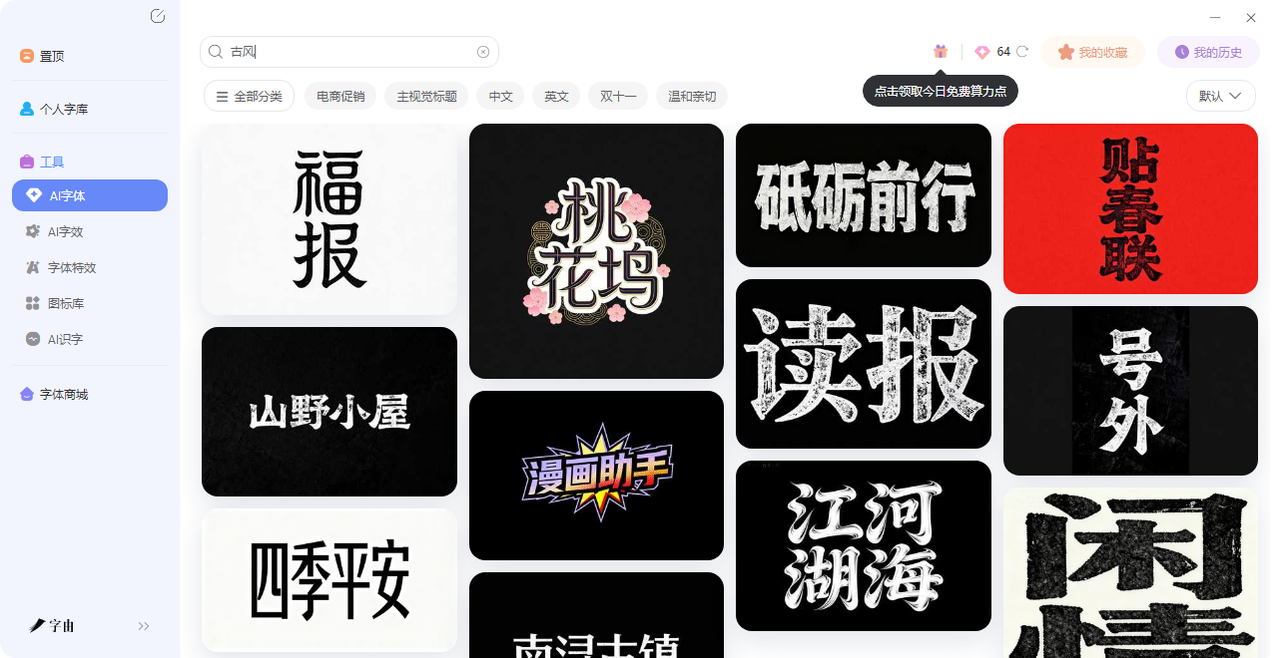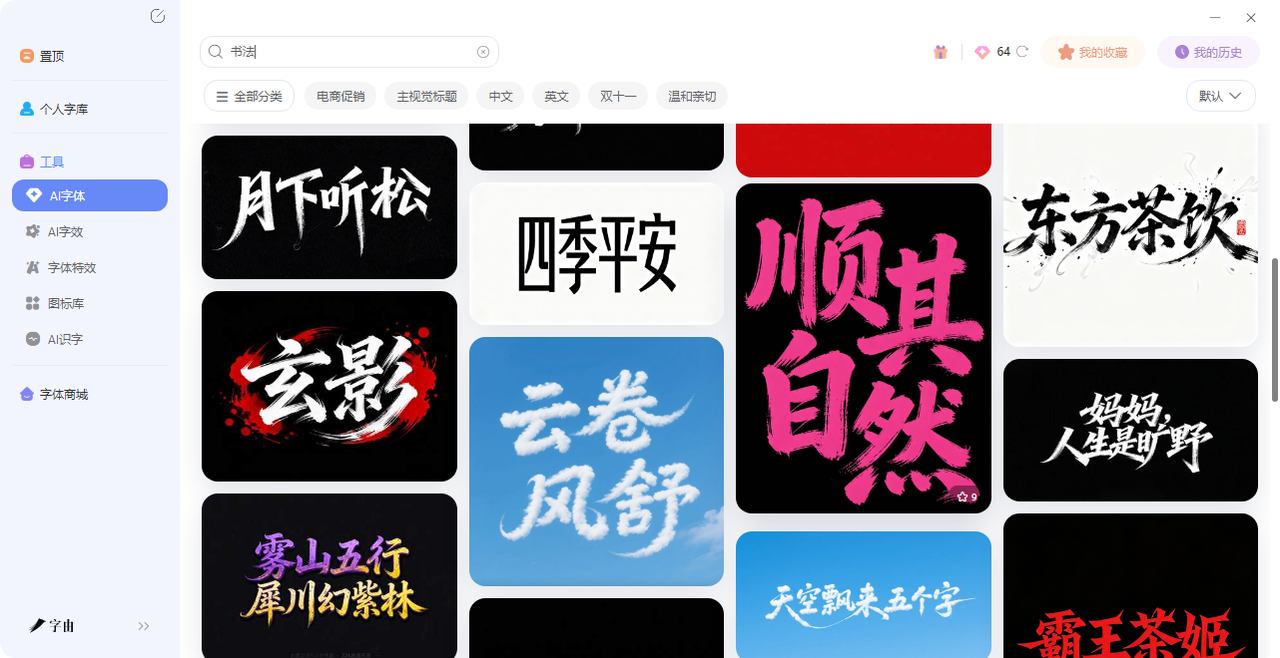
国潮艺术字、中式包装字体、古风Logo…一个网站全搞定
当你的甲方和你说想要国潮字体的时候,脑子里浮现出那种墨韵十足的书法标题,翻遍字体网站,要么是电脑味太重的“书法体”,要么是授权不明的免费字。想做一张国潮海报,标题想要那种笔锋凌厉、墨迹飞白的效果,自己不会写毛笔字,请人写又来不及。想做古风Logo,试了几十款字体,总觉得少了点味道,其实,古风书法字AI生成这件事没那么难,今天我就给大家推荐一款能够一站式解决国风字体需求的网站——字由。它的AI字体功能里藏着大量古风书法模板,输入文字,选个模板,几十秒就能拿到一张自带墨香的艺术字。做国潮设计、中式包装、古风Logo,一个网站全搞定。
字由的“AI字体”功能,不是让你自己去调参数、做设计,而是把成千上万种艺术字效果做成了模板。你只需要输入文字,选一个顺眼的模板,点一下生成,就能拿到一张高清艺术字图片。尤其值得一提的是,它的古风书法类模板,数量多、风格全,几乎覆盖了你做国潮设计可能需要的所有方向。接下来我会把AI字体里面出现的一些我觉得比较好用的古风书法模板分类整理一下,方便你以后快速找到。
节气、季节类模板:
- “万物生长”:这个模板墨色有浓淡变化,适合做春季主题的海报、农产品包装、自然品牌Logo。
- “冬去春来”:字体偏行草,连笔流畅,适合做跨年、春节、四季主题的设计。
- “东极岛”:带着一点岛屿的辽阔感,笔画粗犷但不失韵味,适合做旅行目的地、民宿、海产品的包装或宣传物料。
- “芳华国色”:这四个字偏女性化,笔画柔美,墨迹细腻,适合做化妆品、汉服、国风礼盒的包装标题。
- “糖瓜粘”:这个名字很有意思,字体圆润可爱,带着童趣,适合做年货、糖果、传统小吃的包装。
励志、祝福类模板:
- “暴富”:粗笔大字,墨色饱满,视觉冲击力强。这两年“暴富”是年轻人的热门心愿,用在红包封面、新年礼盒、潮牌联名上,特别讨喜。
- “贴春联”:这组模板模仿了传统春联的书写风格,笔画方正有力,适合做春节海报、对联、福字贴设计。
- “共赴新年”:字体连笔自然,带着一种“一起往前走”的动感,适合做跨年活动、年会邀请函、新年礼盒。
- “新春贺喜”:标准的贺岁书法,笔画圆润喜庆,适合做春节促销、红包封面、节日祝福卡片。
- “元旦”:简洁有力的两个大字,适合做元旦倒计时海报、日历封面。
- “中国结”:这个模板不只是字体,还融入了中国结的装饰元素,文字本身就像编出来的一样,特别适合做春节、中秋的传统节日设计。
武侠、江湖类模板:
- “剑刀矛”:这个模板笔画有力,带着杀气。适合做武侠游戏、兵器主题的包装、格斗赛事海报。
- “再走西游”:字体偏行草,笔画张扬。适合做西游记题材的文创、游戏、影视海报。
- “君有云”:像仙侠小说里的门派题字。适合做仙侠游戏、国风音乐专辑封面。
- “人中之龙”:笔画雄浑,气势磅礴,适合做竞技类游戏、电竞战队Logo、励志类书籍封面。
- “师父”:笔画厚重但不失亲切,适合做武术学校、传统文化课程的宣传物料。
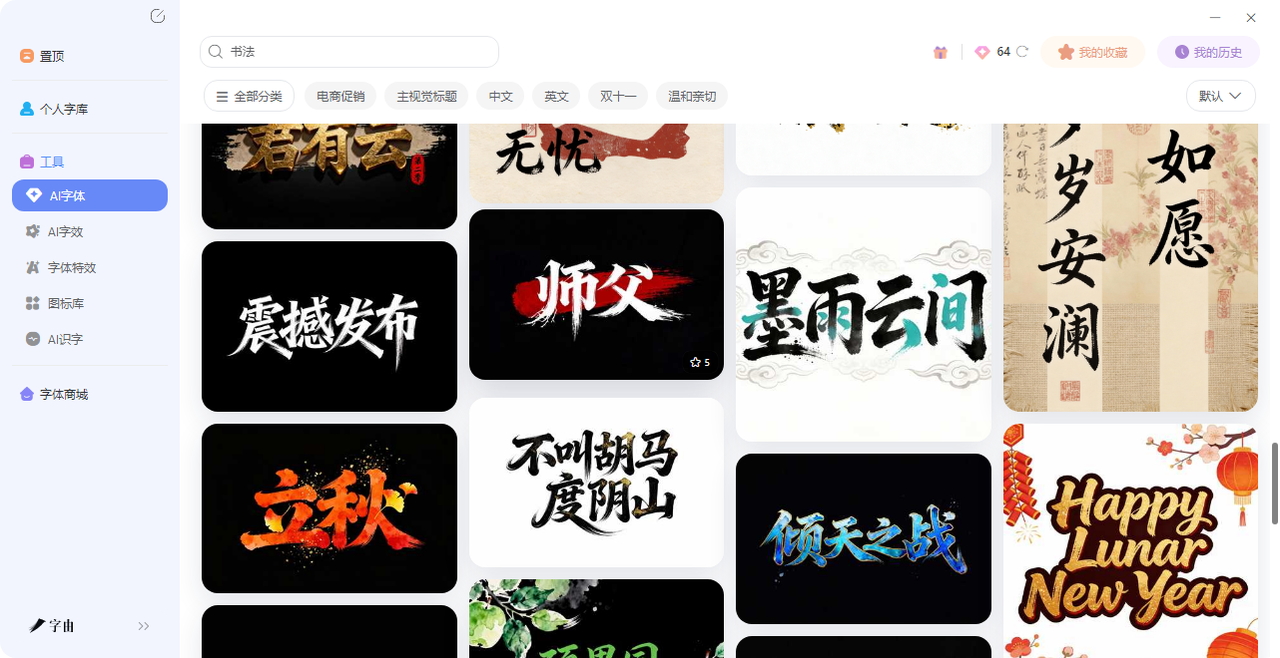
其他模板推荐:
- “黑川”:这两个字笔画粗重,墨色浓黑,带着一种冷峻的工业感。适合做暗黑风格的游戏、潮牌Logo。
- “震撼发布”:这个模板字体夸张,笔画向外扩张,像爆炸效果一样,适合做新品发布会海报、游戏上线公告。
- “卓越不凡”:字体端庄大气,适合做高端品牌、教育机构的宣传海报。
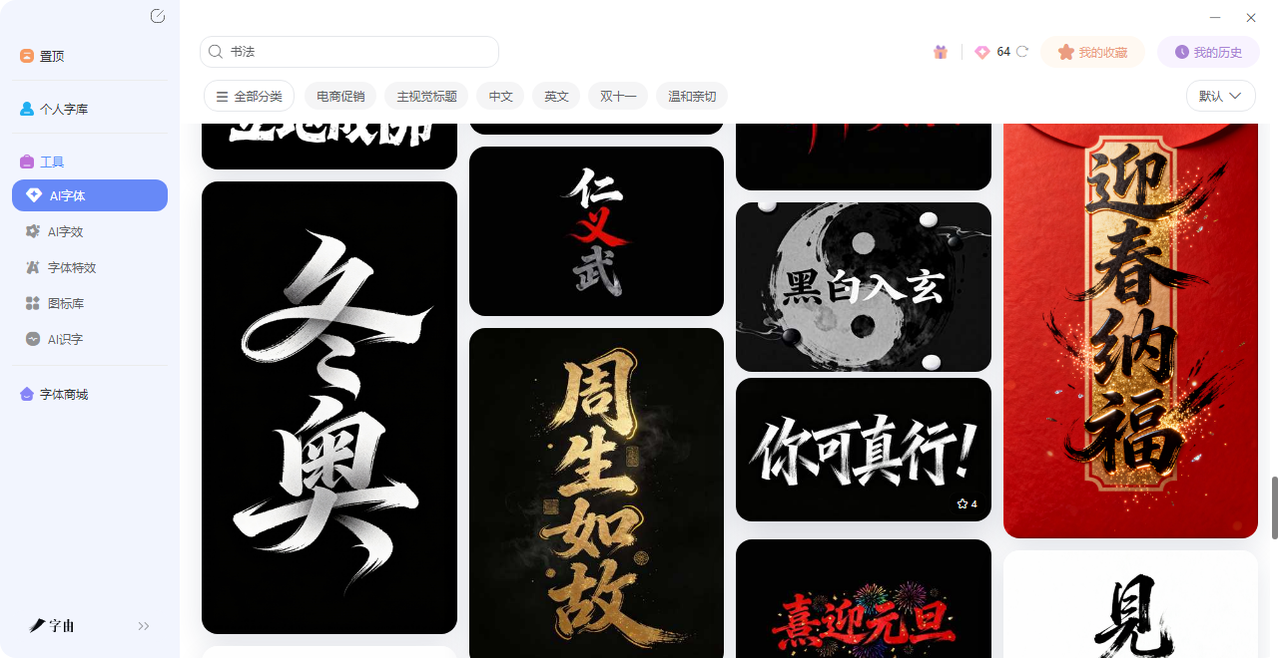
当然以上这些只是截图里展示的一小部分,你在字由的AI字体页面搜索“书法”“国潮”“古风”“毛笔”等关键词,还能找到更多。
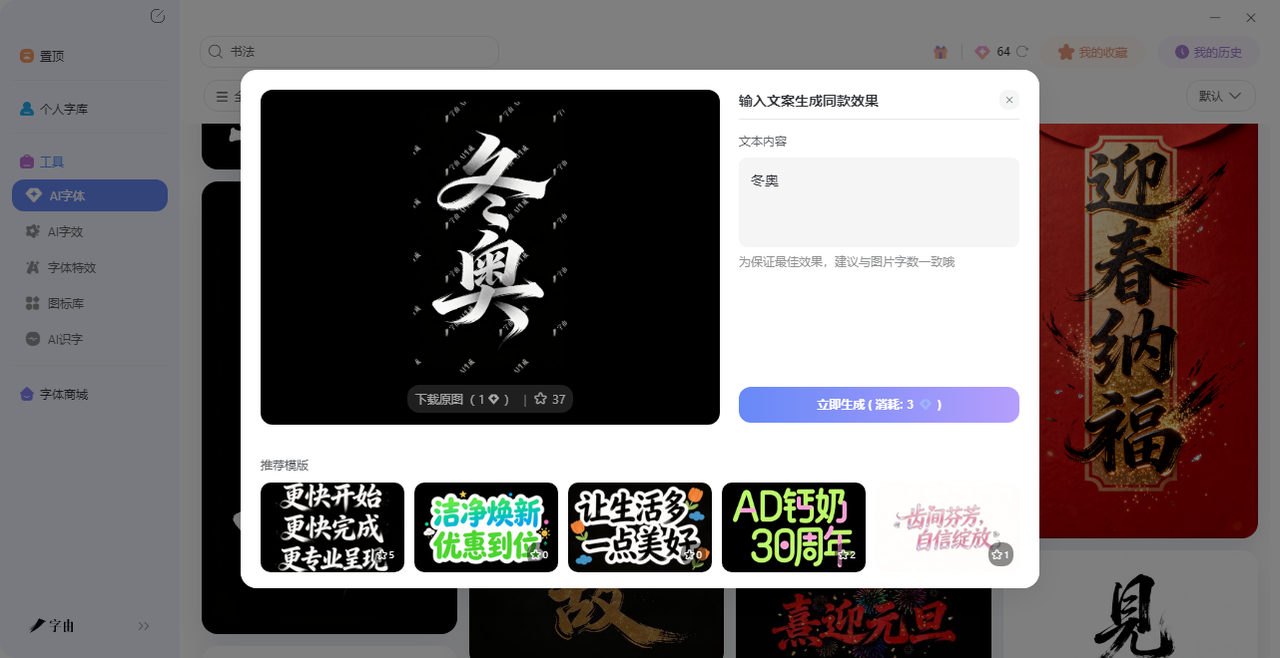
3、AI字效/字体特效功能
如果你已经有了基础字体,或者从字由的字体库里挑了一款现成的书法体,想给它加点特效,可以用字由的【AI字效】功能。它内置了多种特效模板,其中有不少适合古风的效果。如果这里还是没有你喜欢的你可以去试试字体特效找找看有没有你喜欢的特效。
上面提到的这些古风书法模板,可以应用的场景非常多:
- 国潮海报:比如“万物生长”做春季营销海报,“震撼发布”做新品上市海报。
- 中式包装:茶叶、白酒、糕点、文创产品的包装标题,用“芳华国色”“糖瓜粘”“东极岛”都很对味。
- 古风Logo:茶室、汉服店、书院、武术馆,用“君有云”“人中之龙”“师父”做品牌标识,很有辨识度。